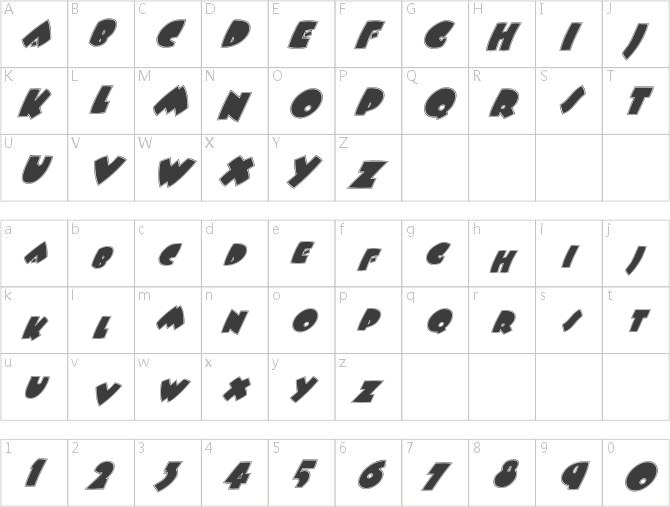
FZ JAZZY 9 CONTOUR ITALIC
FZ JAZZY 9 CONTOUR ITALIC介紹
FZ JAZZY 9 CONTOUR ITALIC字體字庫是一款讓人賞心悅目、百看不厭的英文字體,適合各類廣告和產品包裝設計應用,字體大小0.07MB,格式為ttf字體,上傳用戶是迷路的豬,作者/版權方為未知